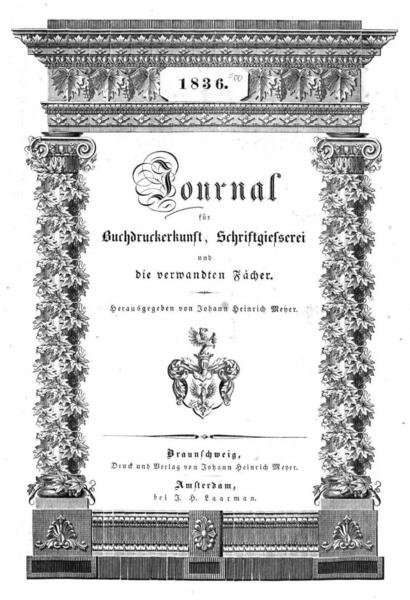
Das »Journal für Buchdruckerkunst, Schriftgießerei und die verwandten Fächer« war eine Fachzeitschrift, die zwischen 1834 und 1919 erschien.
Der Herausgeber, Drucker und Verleger war zu Beginn Johann Heinrich Meyer aus Braunschweig. Er stammte aus einer alten Buchdruckerfamilie, die bereits seit 1610 in Lemgo tätig gewesen war. Sein Ururgroßvater Heinrich Wilhelm Meyer war 1707 nach Braunschweig gezogen und hatte dort eine Druckerei übernommen. Unter der Leitung seiner Mutter trat Johann Heinrich Meyer in die väterliche Buchdruckerei ein. Er entwickelte hohe Ansprüche an die Typografie und erweiterte seine Kenntnisse durch Fachliteratur und Bildungsreisen zu Druckereien, Maschinenwerkstätten und Bibliotheken in Deutschland, den Niederlanden, Frankreich und Dänemark. Als Meyer das Journal für Buchdruckerkunst gründete, war er 22 Jahre alt.
Die ersten Ausgaben erschienen monatlich in einer Auflage von 400 Stück. Ab 1845 kam die Zeitschrift zweimal monatlich und ab 1860 wöchentlich heraus. Die Auflage war mittlerweile auf 1200 Exemplare angestiegen. Meyer konzipierte das Heft als eine Mischung aus historischen und praktischen Informationen. So nahm die Drucktechnik und die Entwicklung der Schnellpressen der Zeit inhaltlich einen hohen Stellenwert ein. Aber auch sozialpolitische Entwicklungen der Branche und die Pressefreiheit wurden thematisiert. Neben Abbildungen von Drucktechnik wurden auch regelmäßig Schriftmuster in die Hefte integriert bzw. wurden beigelegt.
Mit der wachsenden Bedeutung für die Branche wurde das Journal ab 1886 offiziell zum Organ der »Deutschen Buchdruckergenossenschaft« sowie des »Deutschen Buchdruckervereins«. Später kommt noch die »Innung des Hamburgischen Buchdruckerprinzipals-Vereins« dazu.
Die maßgeblichen Herausgeber bzw. Redakteure waren:
- Johann Heinrich Meyer (1834–1863)
- Theodor Goebel (1871–1979)
- Hermann Smallian (1879–1881)
- Ferdinand Schlotke (1881–1901)
Zu Beginn des 20. Jahrhunderts schwindet der Erfolg und Einfluss des Heftes und es kommt zu vielfachen Wechseln der leitenden Redakteure. 1920 wird es vom Verlag des »Deutschen Buch- und Steindruckers« erworben und diesem Heft angegliedert.